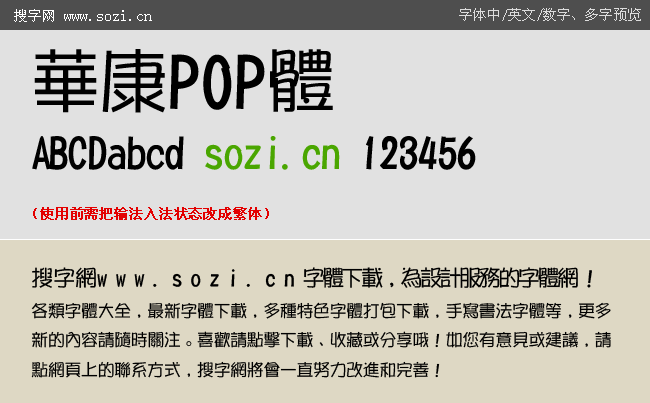
華康POP繁簡完全版
搜字網(wǎng)提供一款華康POP繁簡完全版字體下載,華康POP繁簡完全版是一套廣告專用字體,字形效果和形象明確,讓人難忘,中和的外形,讓它使用范圍非常廣,適合標(biāo)題設(shè)計(jì)、海報(bào)設(shè)計(jì)、招牌設(shè)計(jì)等廣告宣傳使用。
- 風(fēng)格類別: 海報(bào)POP體